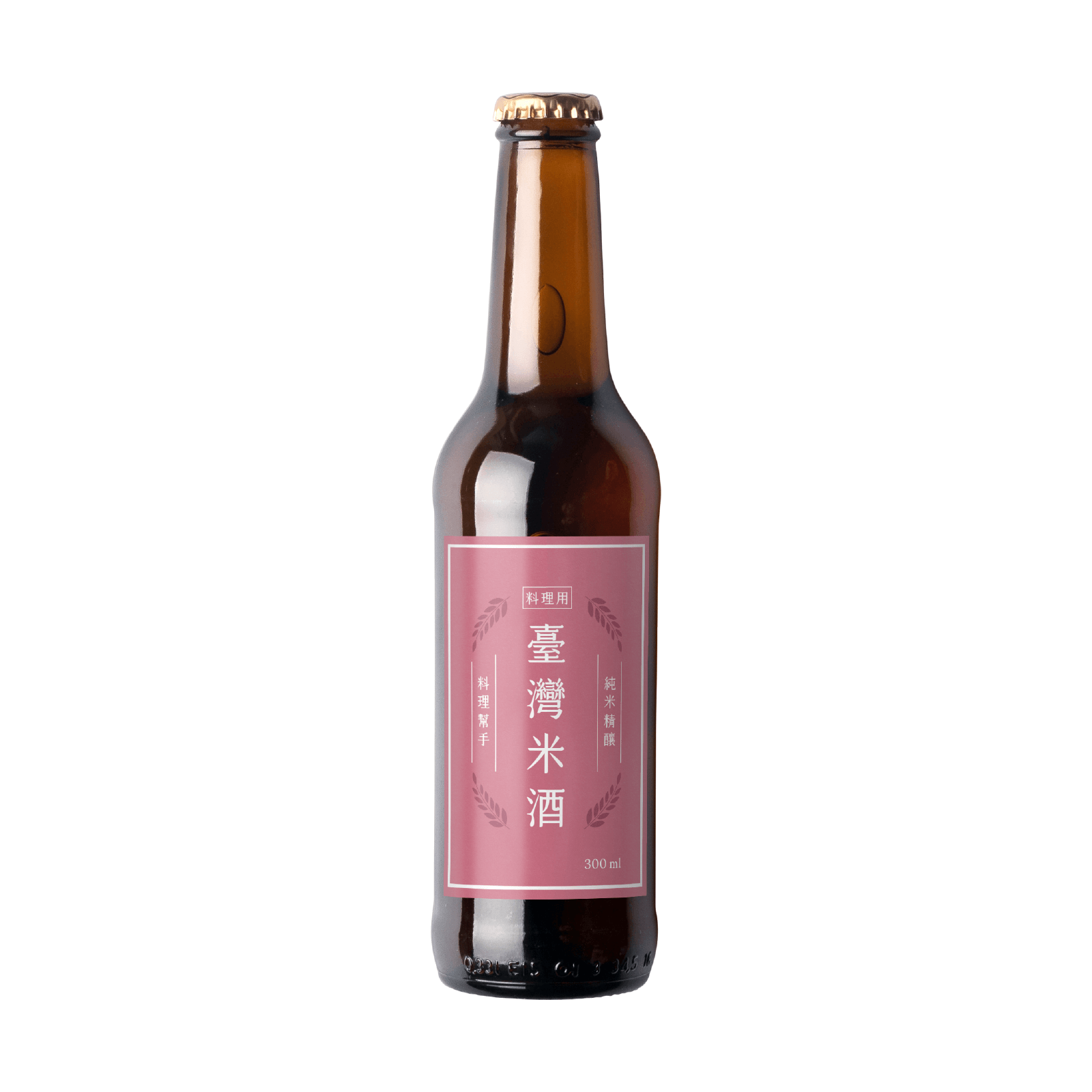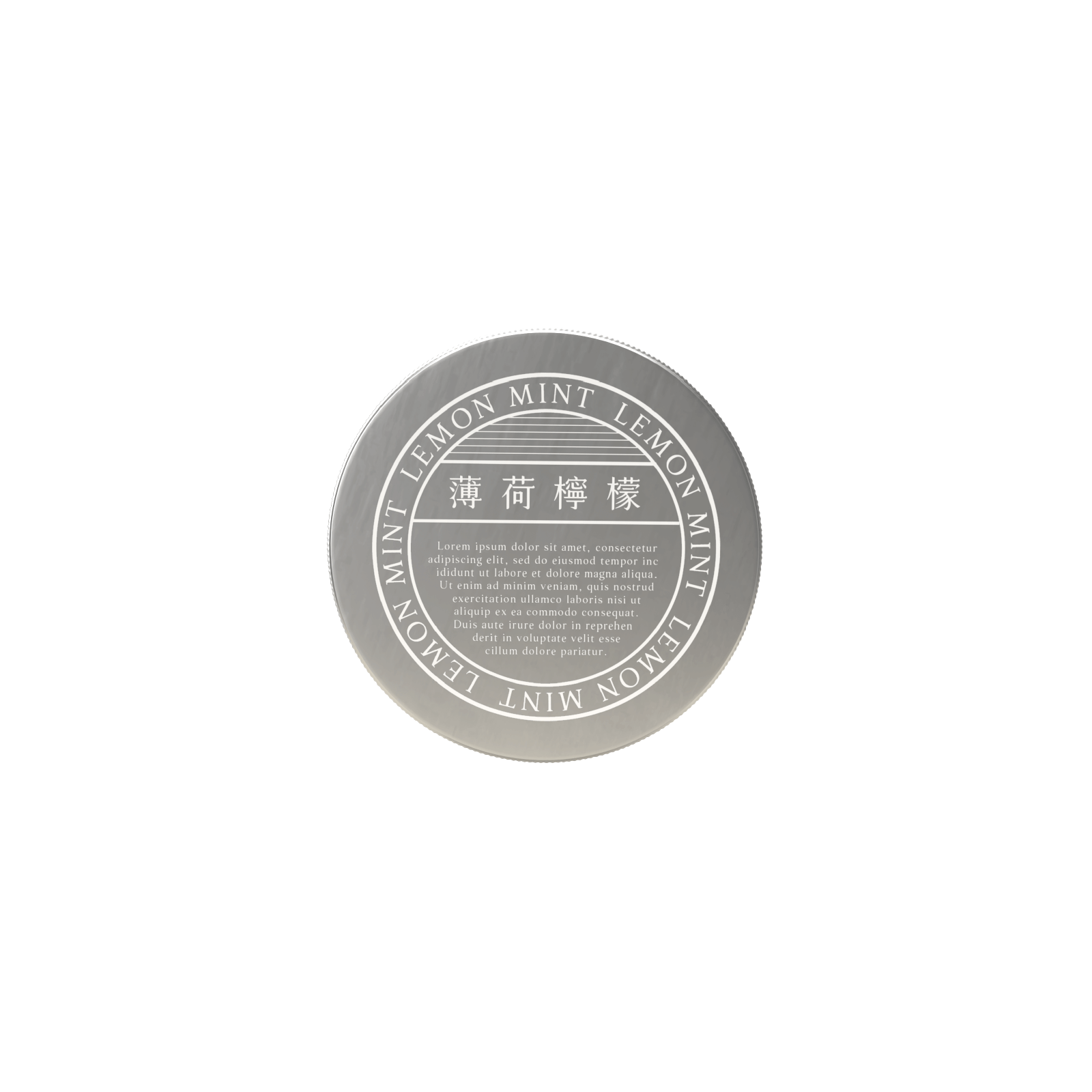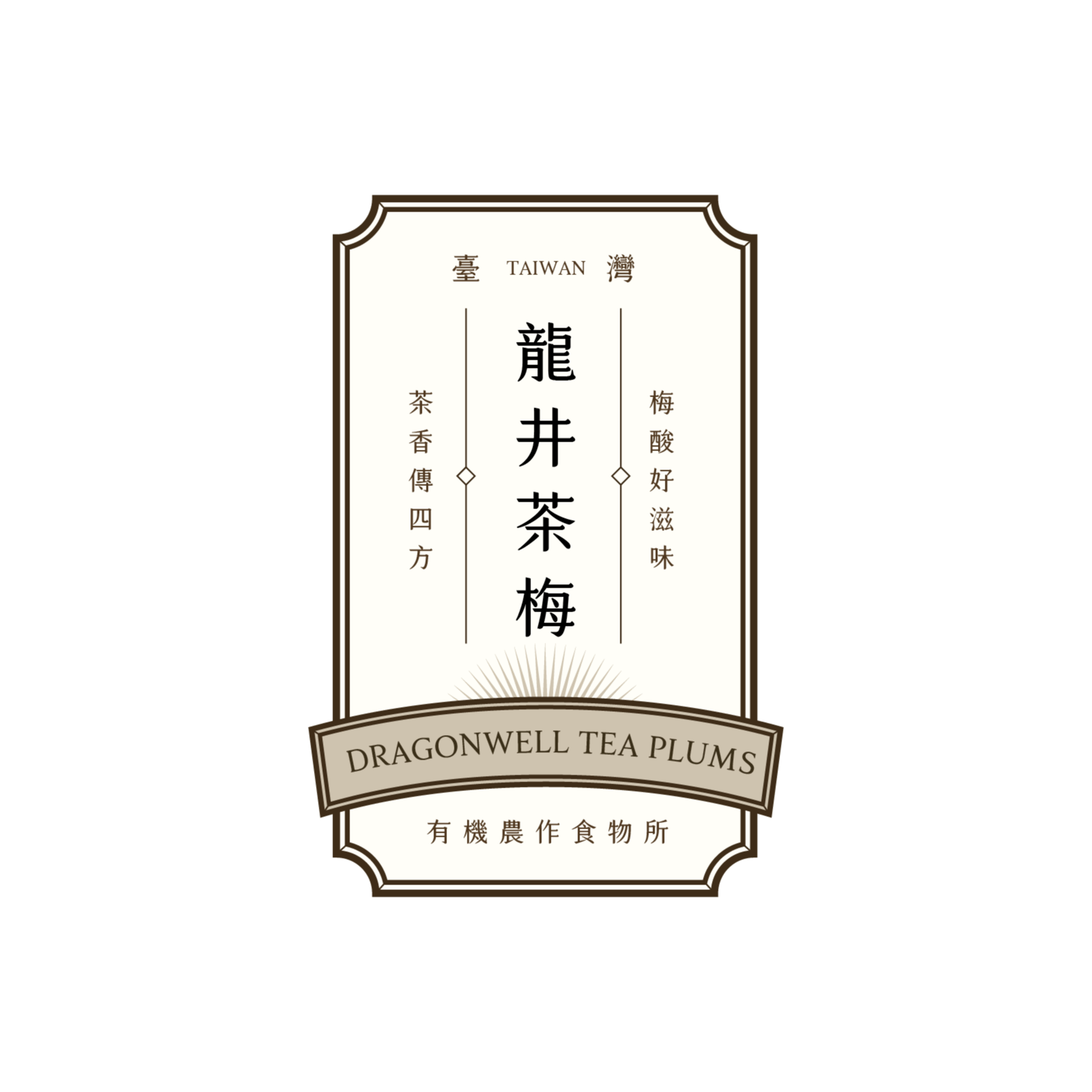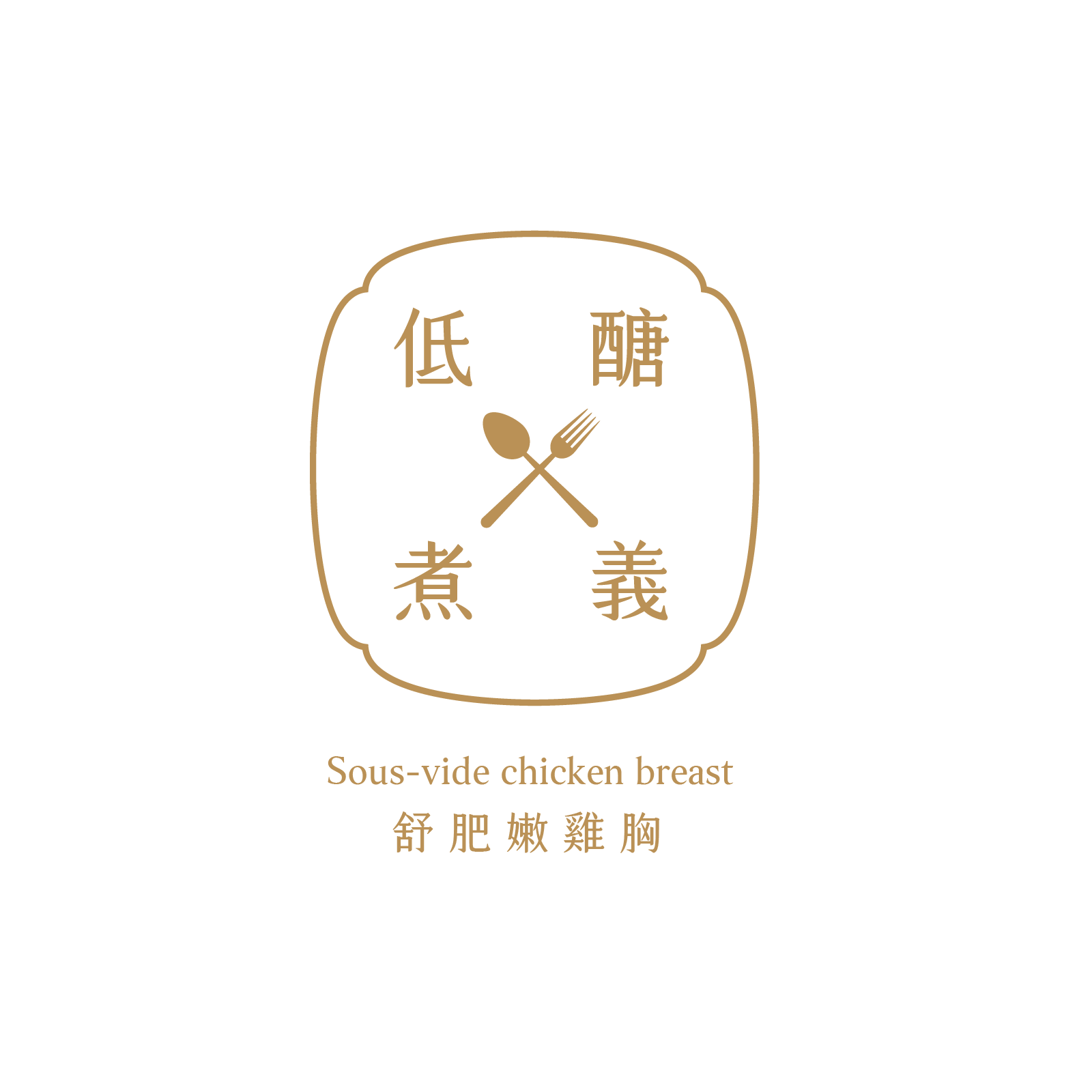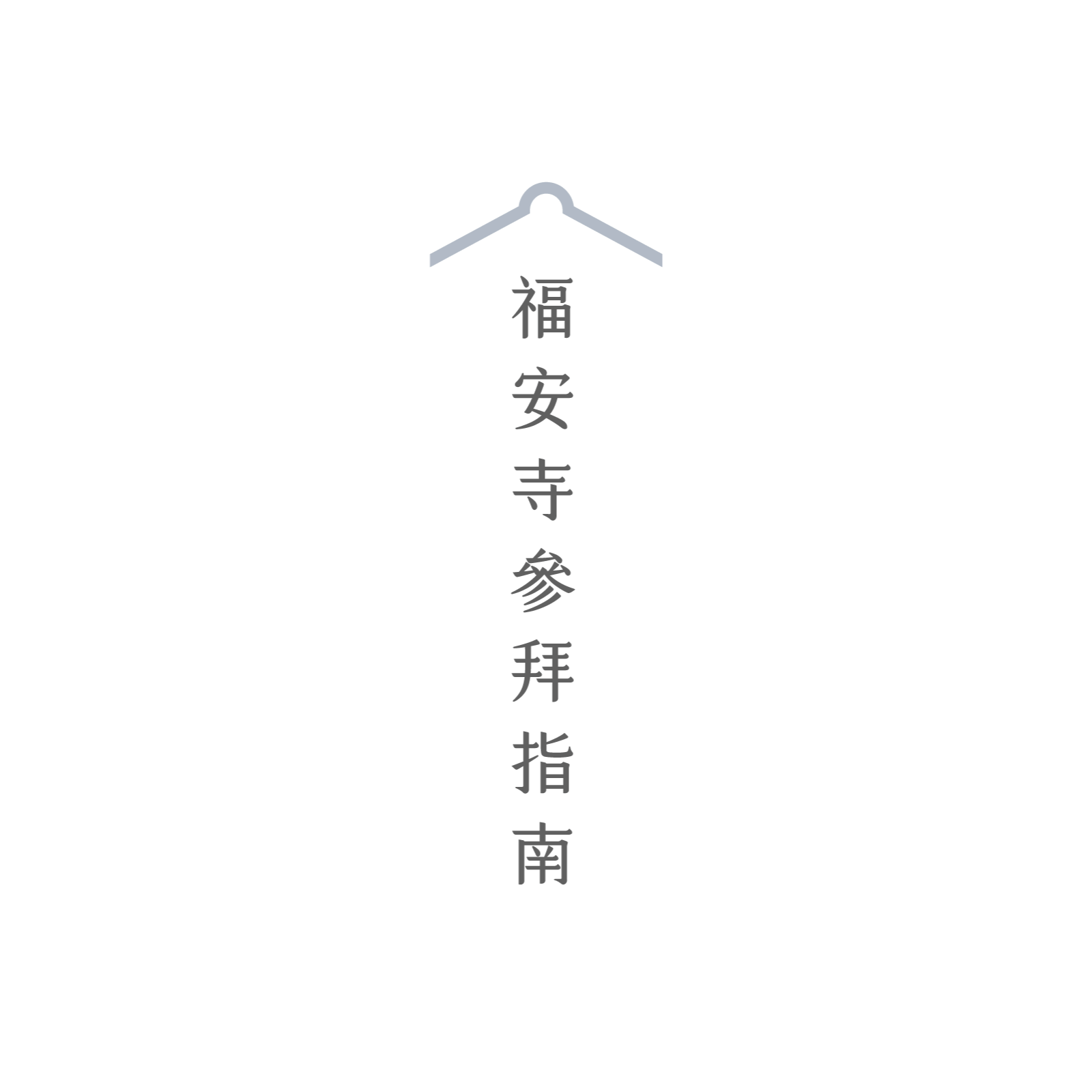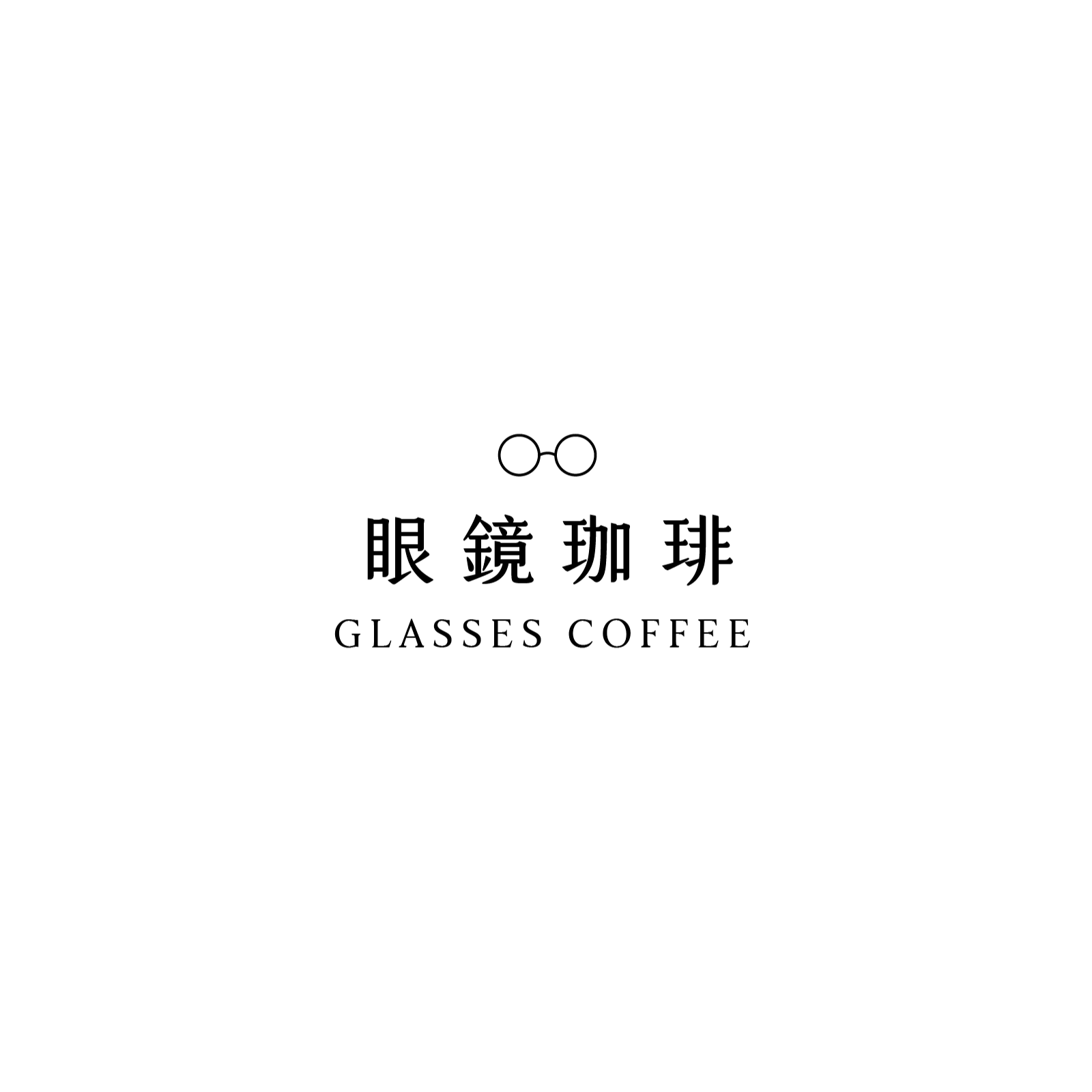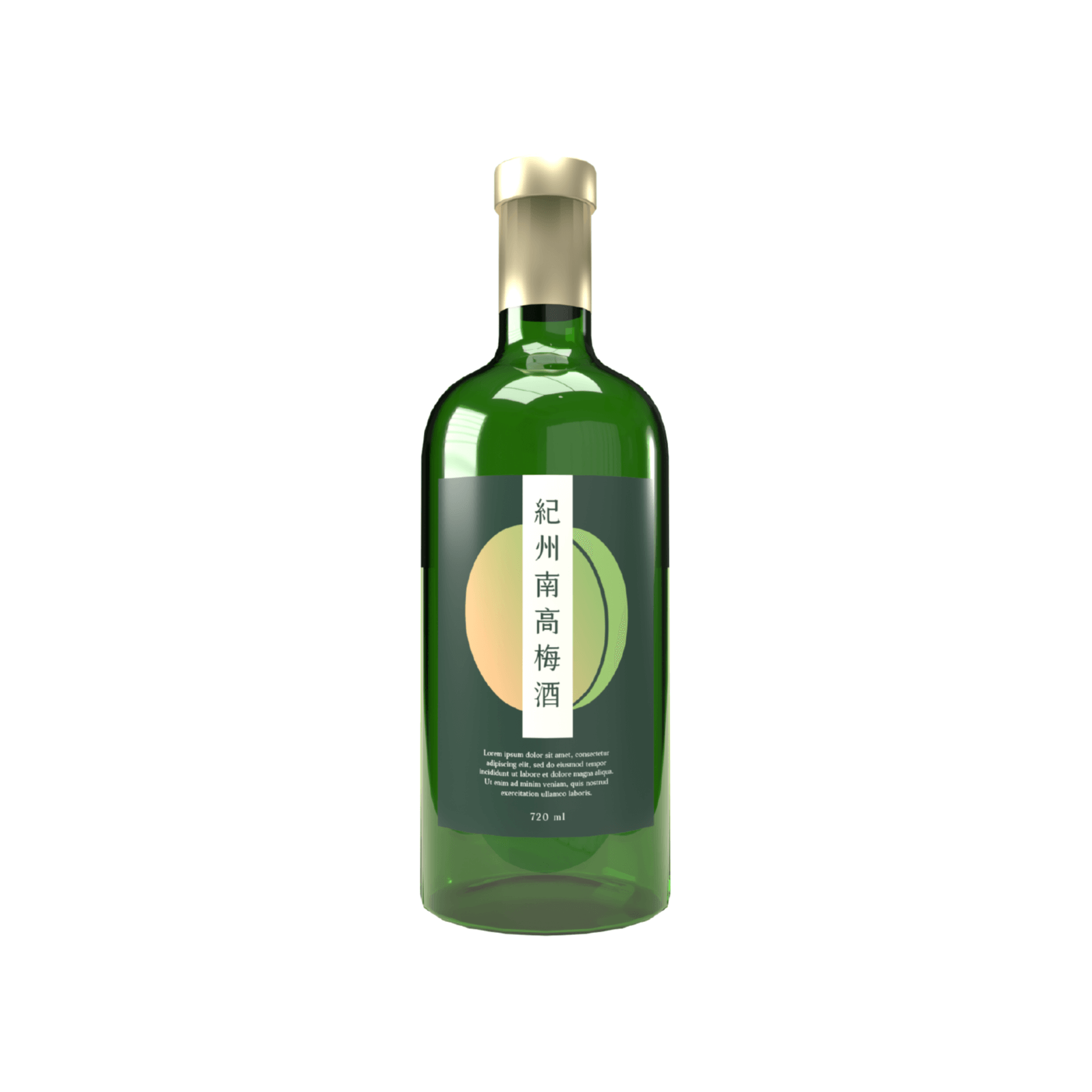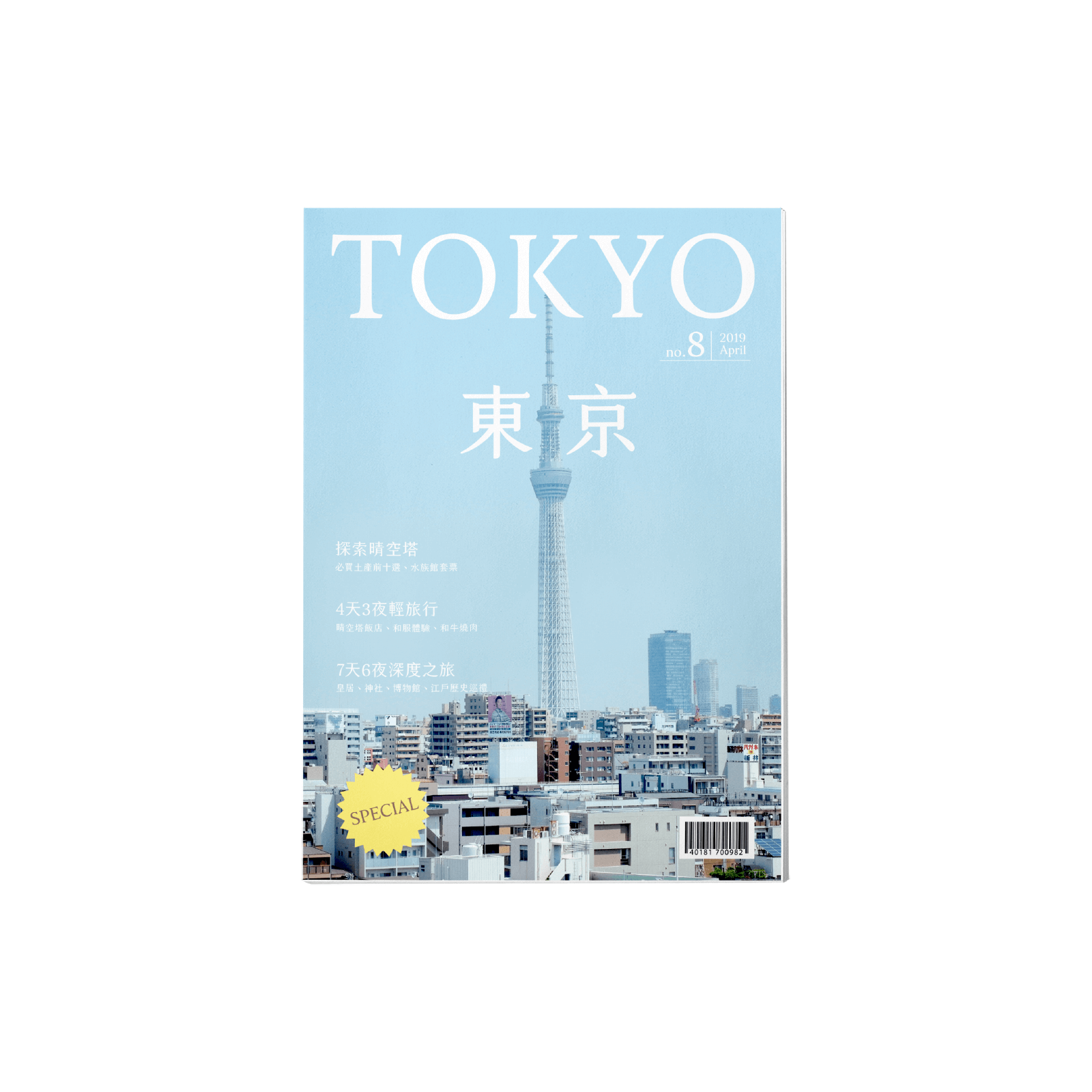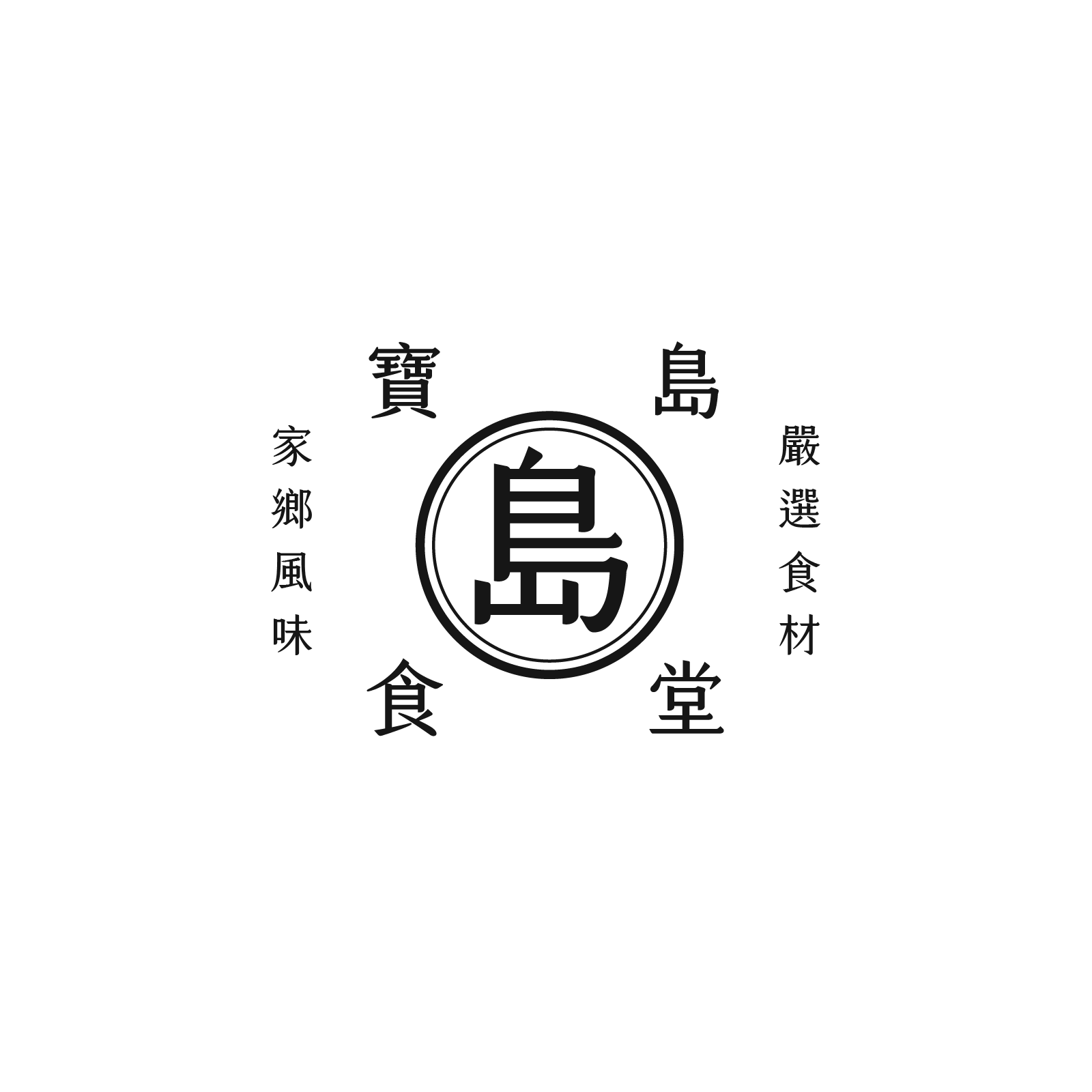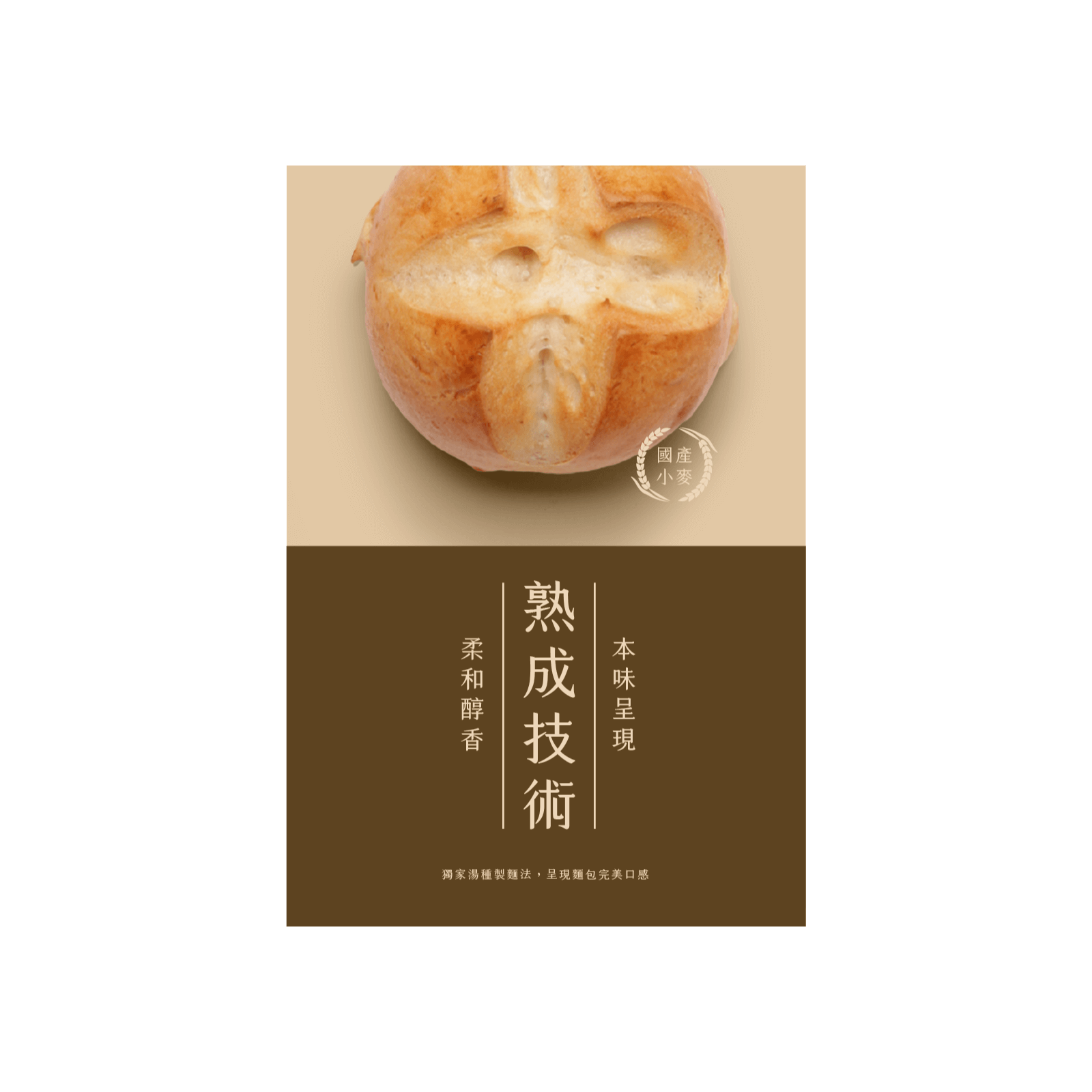
凝書體
源自生活簡單即美
凝書體
輕鬆排版質感倍增
美
橫筆尾端翹起,如凝霜 點似甘露,溫潤飽滿 結字穩固,卻有流暢韻味 漢字、歐文同樣優雅
融合楷體的韻味
與明體的書卷氣
以明體字的骨架為基底,融入書寫的筆韻,讓文字更具溫度與人文氣息
橫筆尾端
如凝霜般翹起
如沾於指尖的凝霜,橫畫收筆設計有柔美的曲線,亦有向上抬起的力道。
渾圓飽滿的
點筆設計
漢字的「點」,是畫龍點睛的關鍵。凝書體點的起筆、收尾皆圓潤,造型飽滿,富有份量。
與漢字風格匹配的
歐文、數字設計
字型裡,每個字符都須具備統一的風格。凝書體用心整合,讓您不必另外切換字型,也可以有風格一致的搭配。
自然留白就是美,風格的事情,交給凝書體。版面簡潔,搭配凝書體就能讓作品流露優雅簡練的氣質。
凝書體 2.0 版本
收錄內容
凝書體 2.0 版本收錄包含漢字、英文、數字、注音、希臘字母、日文假名、香港常用字、常用排版標點與符號共超過 9,000 個字符
風格決定於文字落地的瞬間。 數年準備,是為此一刻的驚艷。
點擊兩次,感受凝書體的優雅氣息。源自生活,簡單即美。把視覺秩序梳理乾淨,剩下的交給字體發揮。你也能透過簡單的編排,做出美麗的文件、簡報與作品。
落實在生活的每一天: 不限於專業作品,就連基本排版也很美,是凝書體的設計初衷。
落實在生活的每一天: 不限於專業作品, 就連基本排版也很美, 是凝書體的設計初衷。
源自生活,簡單即美 小小改變,就能帶來驚艷的改變 精心製作的細節,將為你的作品加分